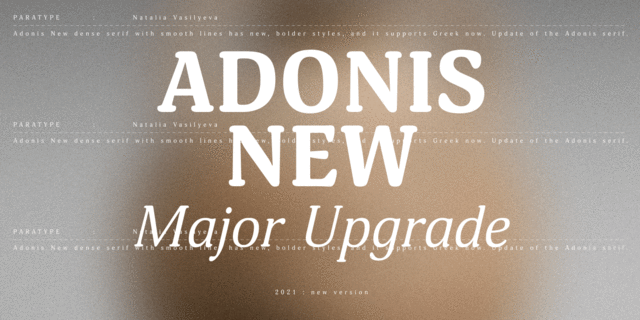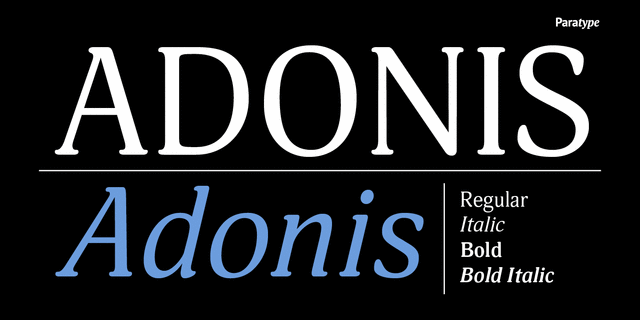
Adonis New — серьёзное обновление антиквы Adonis. В этой компактной антикве с плавными линиями появились новые, более жирные начертания, и поддержка греческого языка. Кроме того, Наталья Васильева переработала рисунок основных начертаний и сделала его более свежим и точным. Adonis New хорошо работает в книжном наборе, особенно в художественной литературе и книгах по гуманитарным дисциплинам. Шрифт выпущен компанией Паратайп в 2021 году.
Мягкий, уютный, умеренный, спокойный, стабильный, устойчивый, универсальный, вежливый, интеллигентный, комфортный, ненавязчивый, ровный, гладкий, мирный, дружелюбный, ясный, удобный, деловой, статичный, сдержанный, современный, экологичный, зеленый, гармоничный, весенний, гуманитарный, органический, красивый, мягкий, убедительный, насыщенный, вкусный, пышный, добрый, приятный, доброжелательный, пластмассовый, приветливый, милый, семейный, домашний